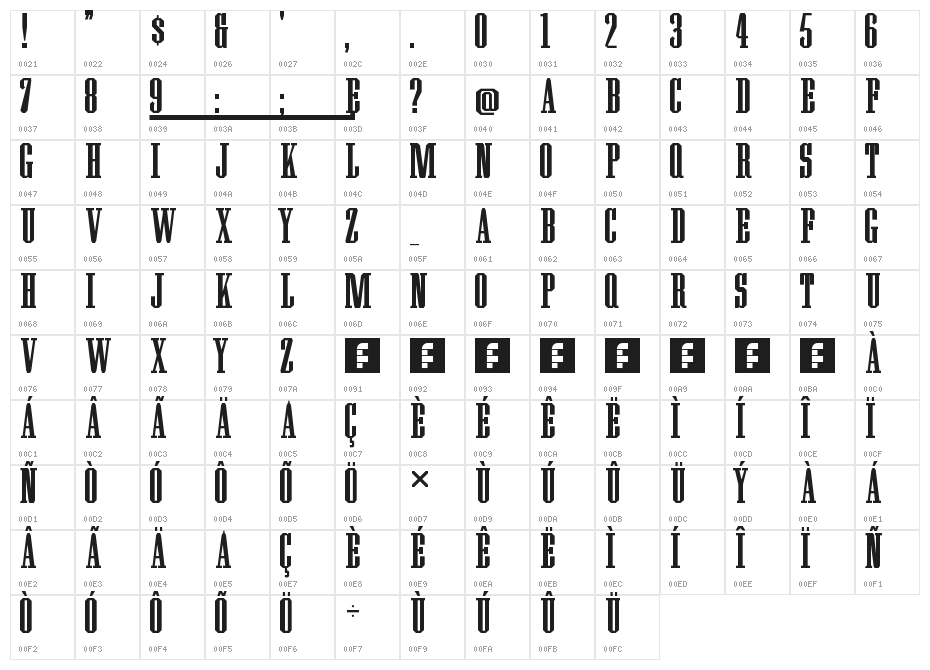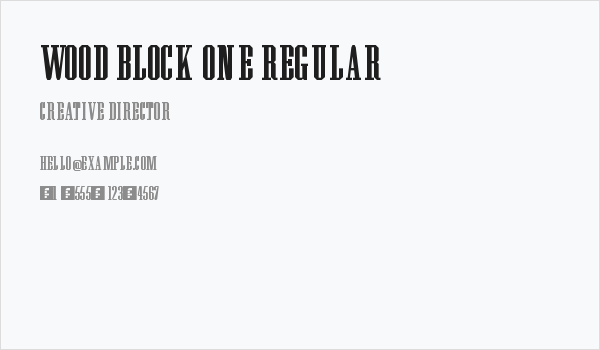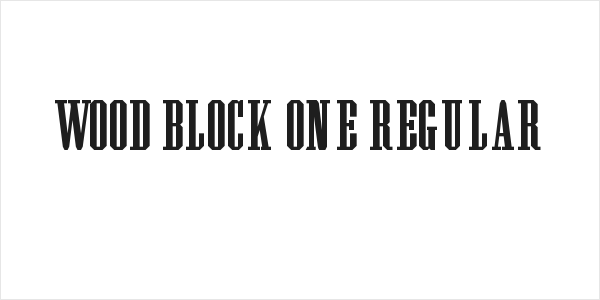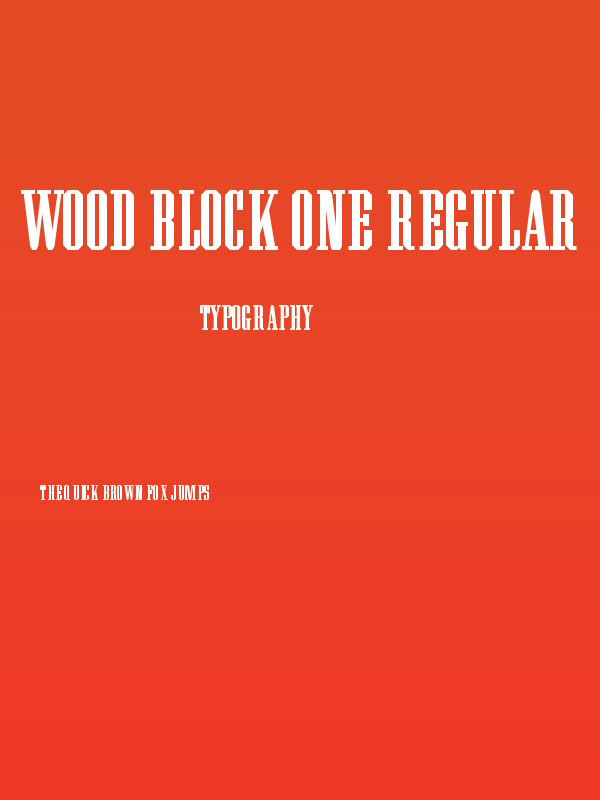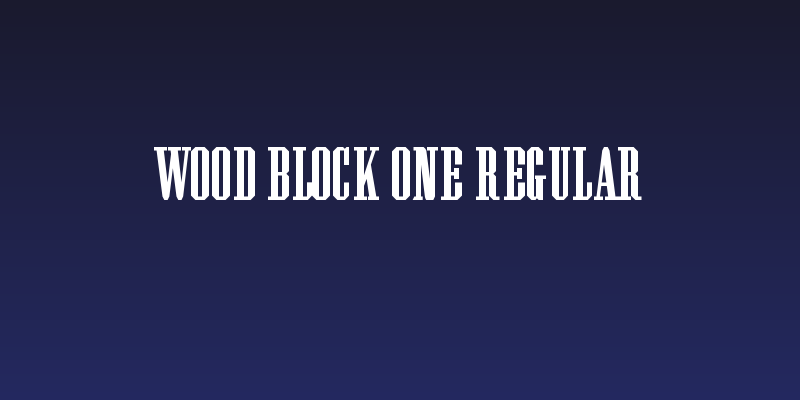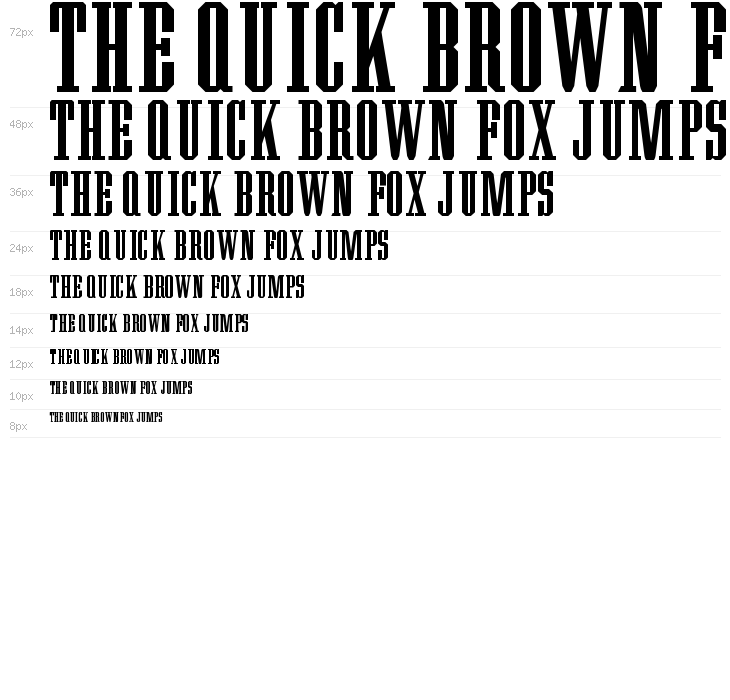
Wood Block One Regular Font
✎ Retro
| الفئات | Retro |
| العرض | Condensed |
| النمط العام | Vintage |
| مشاريع مقترحة | Ideal for vintage posters, signage, branding, and any project needing a bold, industrial look. |